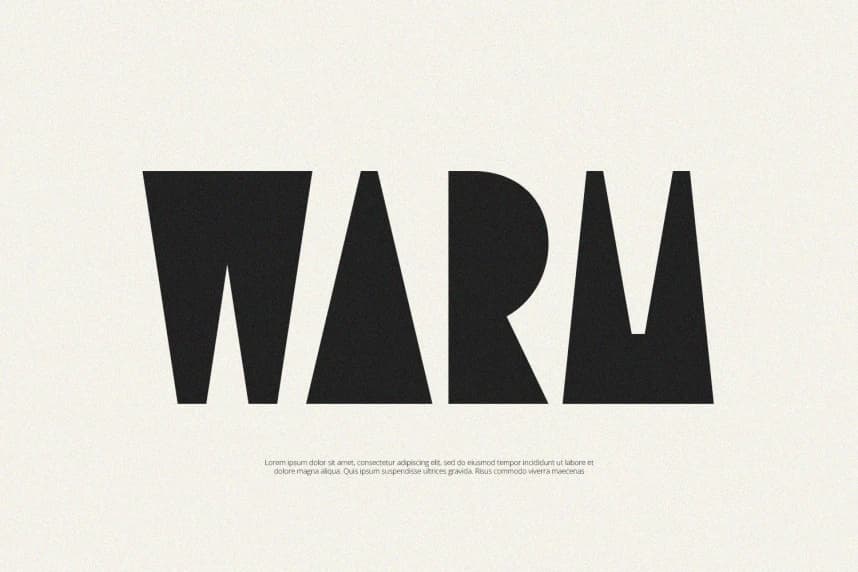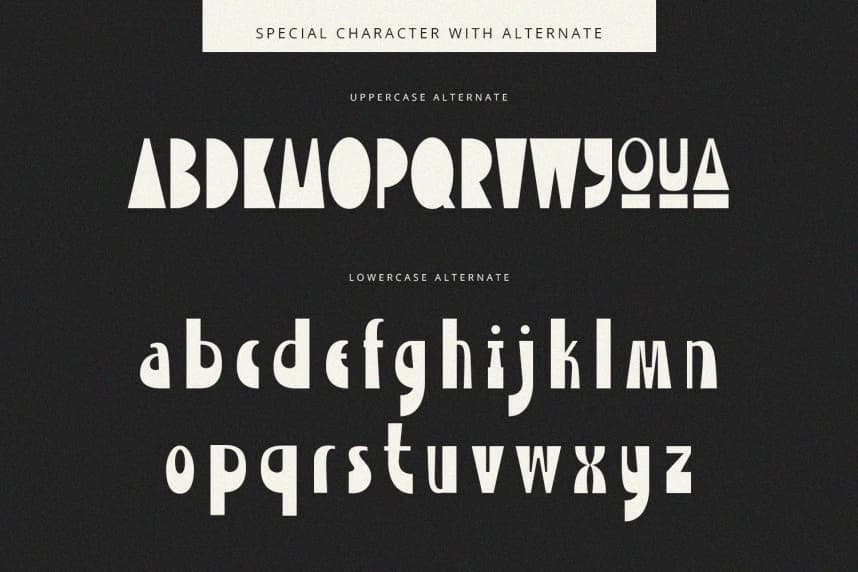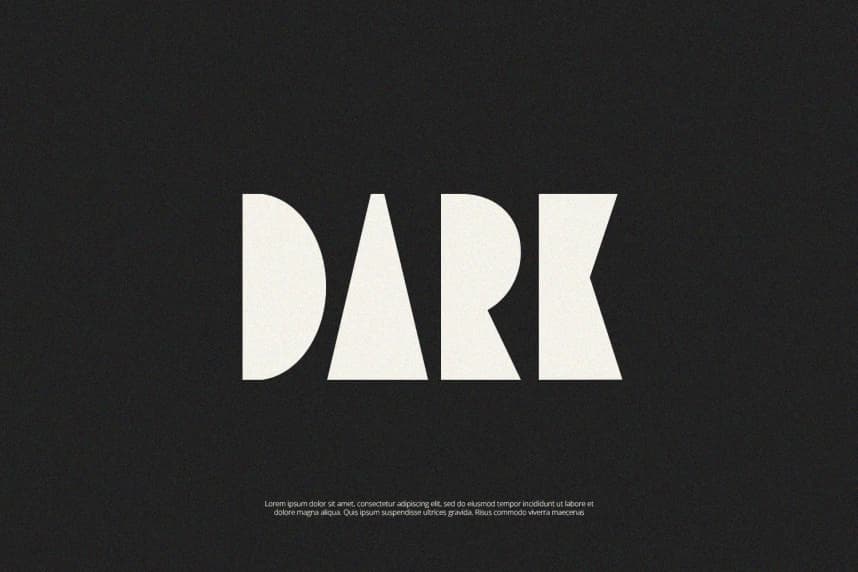
Shardmark – Display Font
Shardmark - Display Font, modern bir hissiyat sunan bir display fontudur. Marka Tasarımı, Logo Tasarımı, Lettering, Logotip, Giyim, Poster, Dergi, Ambalaj, Posterler, Alışveriş Çantaları, Tişörtler, Kitap Kapakları, Fotoğrafçılık, Özel Etkinlikler ve diğer tasarım projeleri için mükemmel bir şekilde
Shardmark - Display Font, modern hissiyatlara sahip bir display yazı tipidir. Marka Oluşturma, Logo Tasarımı, Harf Tasarımı, Logotip, Giysi, Poster, dergi, ambalaj, posterler, alışveriş çantaları, tişörtler, kitap kapakları, fotoğrafçılık, özel etkinlikler ve diğer tasarım projeleri için mükemmel bir şekilde kullanılabilir.